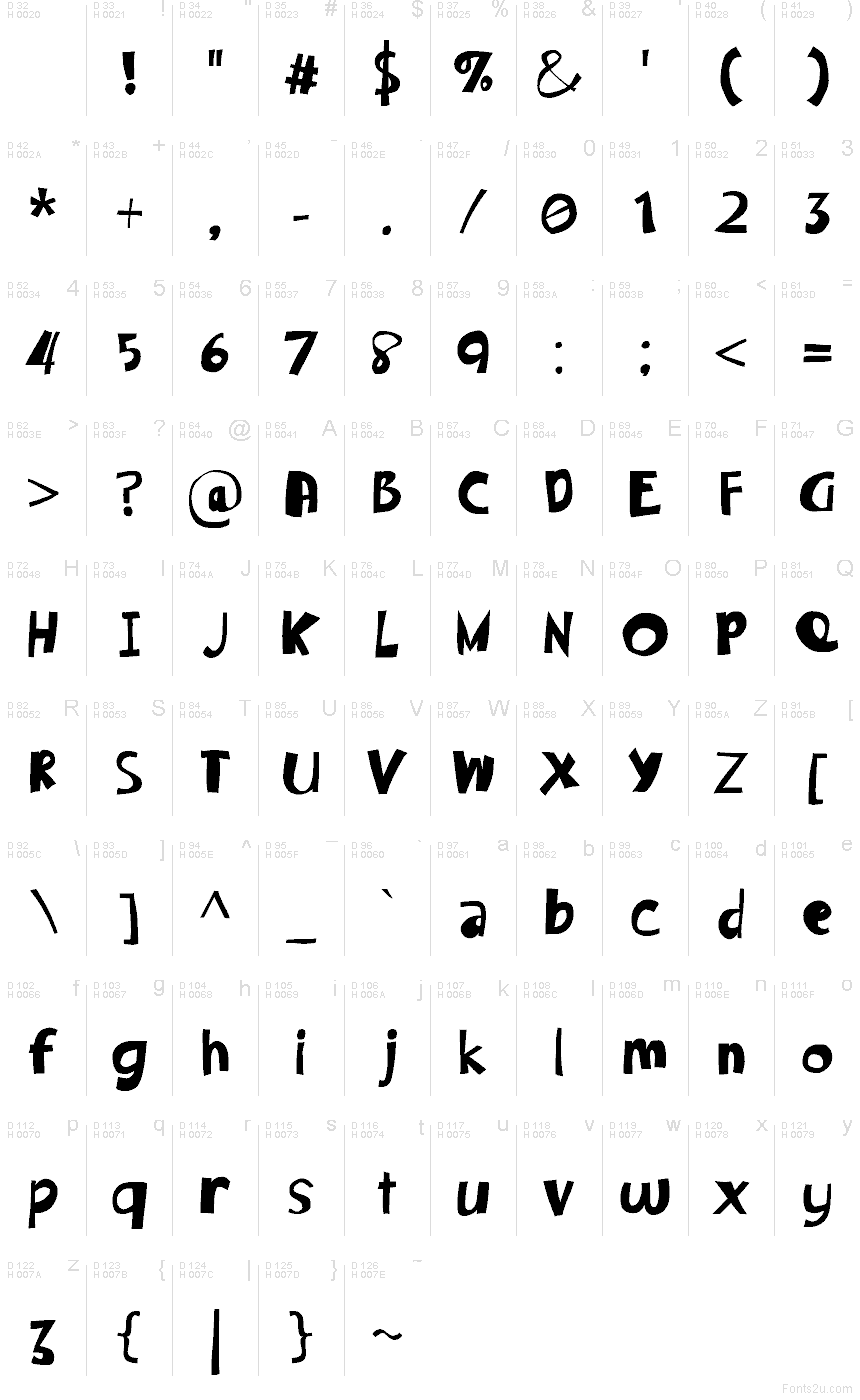
AOW11 Next World Regular
AOW11 Next World é uma fonte display gratuita no estilo comic com uma silhueta robusta e elástica, que faz com que cada letra pareça ligeiramente empurrada, inclinada ou espremida à mão. Essa massa irregular confere às letras uma presença marcante de desenho animado, com formas arredondadas e ângulos rombos que mantêm o conjunto coeso, em vez de caótico.
É nos títulos curtos que a AOW11 Next World faz mais sentido: cartazes infantis, títulos de jogos, designs de autocolantes, convites de festas e miniaturas do YouTube beneficiam do seu ritmo saltitante e desalinhado. As formas encorpadas também dão a embalagens simples ou a gráficos de merchandising um tom de banda desenhada artesanal que pareceria demasiado inquieto em textos longos.